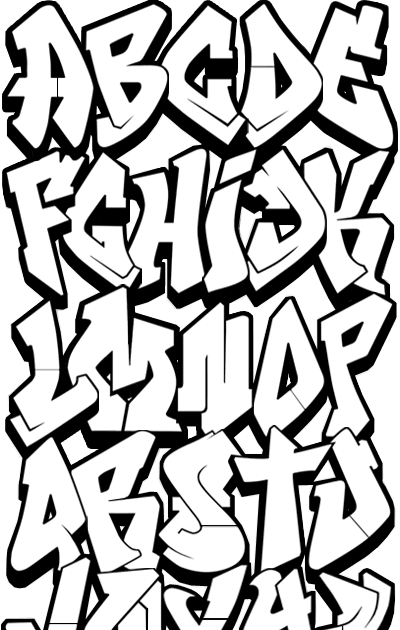
Подборка граффити шрифтов для проектов
Не так просто найти лучшие бесплатные шрифты граффити. Это отчасти потому, что довольно сложно определить, что делает шрифт граффити. Слово «граффити» сегодня означает нечто иное, чем несколько десятилетий назад. Хотя раньше это слово ассоциировалось с нацарапанными, уродливыми и непристойными явлениями и развратами внутри города, рост творческого и вдумчивого (не говоря уже о ценном) уличного искусства изменил взгляд на форму искусства и вывел его в мейнстрим.
Теперь вы увидите работы, вдохновленные уличным искусством, которые охватывают все, от рекламы до оформления альбомов. Рост популярности означает, что в ваших проектах есть множество тематических граффити-шрифтов. С формами от спрей-покраски и брызг до надписей кистью и стилей трафарета, мы получили все это.
Metro Grunge
Metro Grunge — бесплатный шрифт от Peter Olexa, независимого дизайнера из Братиславы, Словакия. Шипение энергии подполья (как метафорического, так и актуального), этот шрифт бесплатный как для личного, так и для коммерческого использования.
Extreme Travel
Extreme Travel Font — это шероховатый шрифт в стиле граффити, созданный колумбийским графическим дизайнером и иллюстратором Луисом Харамильо. Он имеет изобретательный вид, который в основном состоит из белых букв, нанесенных трафаретом из брызг, окрашенных брызгами. Этот демонстрационный шрифт доступен для бесплатной загрузки только для личного использования.
Flow
Созданный болгарским дизайнером Десси Давидовой, Flow «вдохновлен неровностями». Кажется, что он легко находит место между элегантным и вольным стилем, что делает его хорошо подходящим для граффити-проектов.
Broken Wings
Broken Wings — это зубчатая, нервирующая гарнитура от Bdstrd Std, которая включает в себя большие и маленькие буквы, а также стандартные цифры и символы.
Vitruvian Man
Этот шрифт дикий, дикий, дикий: если вы хотите обратить внимание на злобную, вандалистическую сторону граффити-культуры, Витрувианский Человек вполне может быть отличным выбором. Разработанный Checkered Ink, этот шрифт бесплатный только для личного использования.
Youth Fury
Нужно вспомнить оригинальный стиль вандализма граффити? Точно названная Молодежная Ярость вызывает дух недовольной молодежи. Работает колумбийский графический дизайнер и иллюстратор Луис Харамильо, его можно бесплатно скачать только для личного использования.
Sister Spray
Получите беспорядок с этим фантастически грубым и готовым шрифтом, снова от ImageX. Он состоит из полного набора букв в верхнем регистре, окрашенных распылением, а также нескольких строчных букв для выделения, а также брызг, брызг и ударов, чтобы завершить внешний вид. Это бесплатно для личного использования.
The Fresh Prince
Первый шрифт от Team Knorke, The Fresh Prince, дизайн граффити — один из наших любимых. «У нас была идея для этого после некоторого пива и обсуждения о шутливости большинства граффити-шрифтов», — заявляет член команды Феликс Шварце на Behance. «Мы набросали буквы довольно грязные с помощью стандартного фломастера — уличного стиля».
Gang Bang Crime
Дизайнер Maelle Keita — еще один шрифт с полностью заглавными буквами — предлагает два набора, один с другим, а другой без капающей краски Этот шрифт бесплатный только для личного использования.
Polla
Созданный финским дизайнером Юхой Корхоненом, Polla — удивительно грязный шрифт, заполненный пятнами и брызгами, которые действительно оживят ваш текст. Это бесплатно для личного использования.
Damsterdam
Damsterdam, еще один из Juha Korhonen, представляет собой тяжелый шрифт с полностью заглавными буквами, сделанный из толстых, грубых мазков кисти, с кривыми, в шахматном порядке буквенными буквами, которые просто полны энергии.
Bombing
Bombing поражает своим внешним видом и был создан французским дизайнером Квентином Аквилой. Скачайте настоящее граффити, когда будете использовать этот шрифт для своих работ.
Urban Jungle
Смелый и великолепный, этот шрифт, созданный Кевином Кристофером из KC Fonts, идеально подходит для создания плакатов и листовок в стиле граффити. Используйте их, чтобы ваши проекты выделялись из толпы.
Happy Brown Cat
Happy Brown Cat восхитительный будет, возможно, преуменьшением. Большие и упругие шрифты предоставляют неограниченное удовольствие любому, кто использует эти шрифты от LazyPoony.
Ruthless Drippin ONE
Потрясающий дизайн шрифта Mans Greback очевиден в этих отличительных формах букв, которые дают ощущение капающей краски. Если вам действительно нужны шрифтовые теги, используйте этот каллиграфический шрифт.
Незаконный Edding
Этот специальный шрифт был разработан, чтобы придать сжатый стиль зубила. Загружаемые файлы предоставляются широкий набор символов, а шрифты очень удобны для глаз, что облегчает их чтение, сохраняя ощущение граффити.
Зит Граффити
Созданные известным дизайнером Оливье «Zitoune» D, эти блочные шрифты являются смелыми и эффектными. Набор поставляется только заглавными буквами.